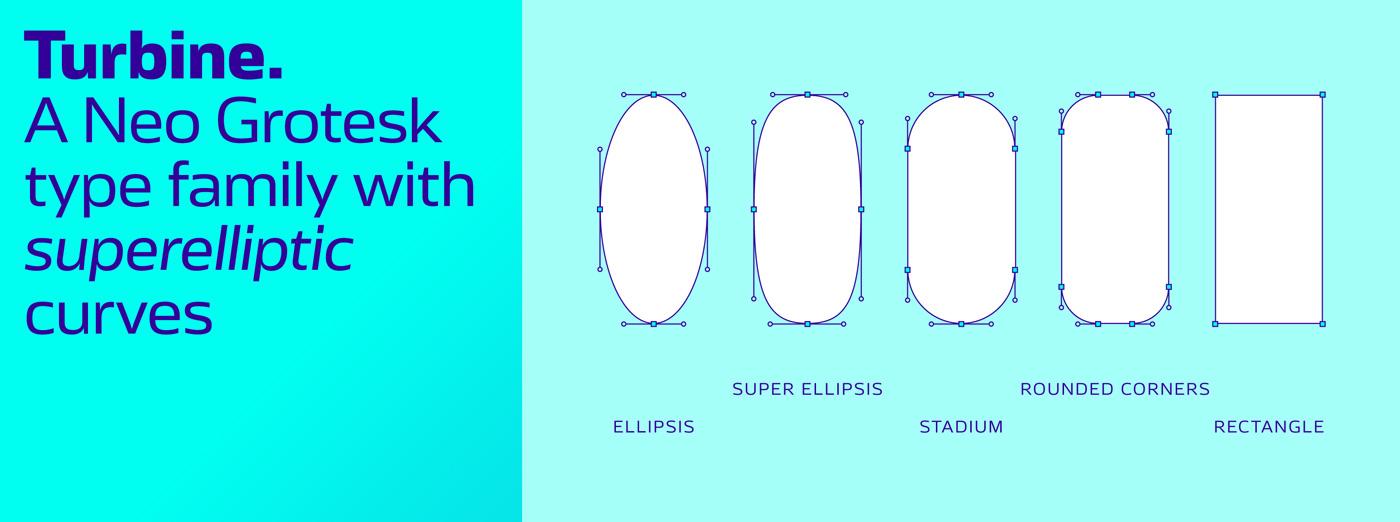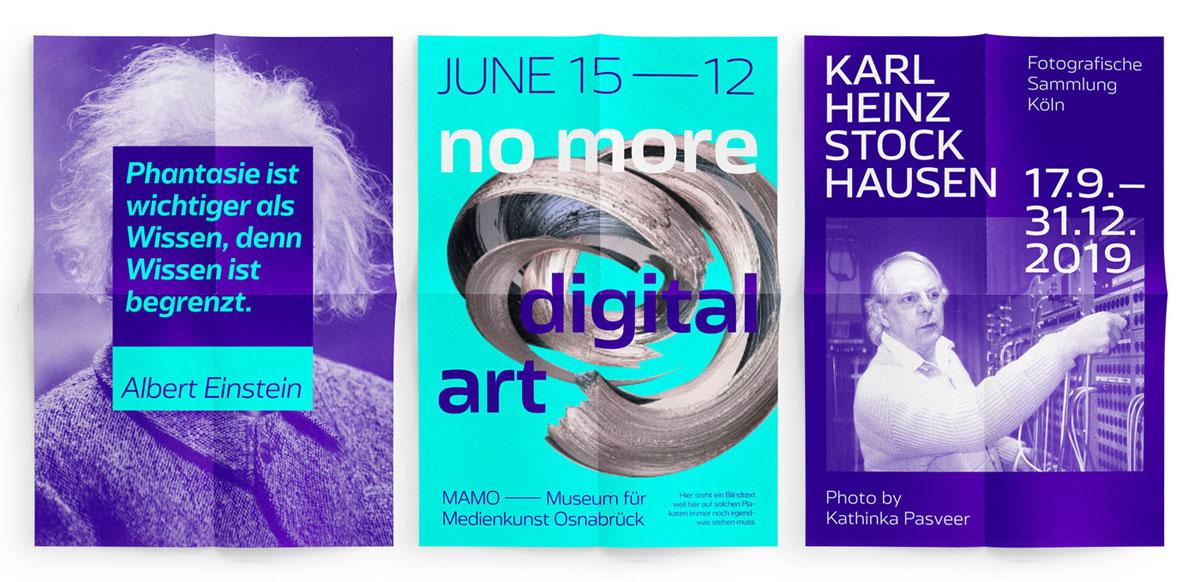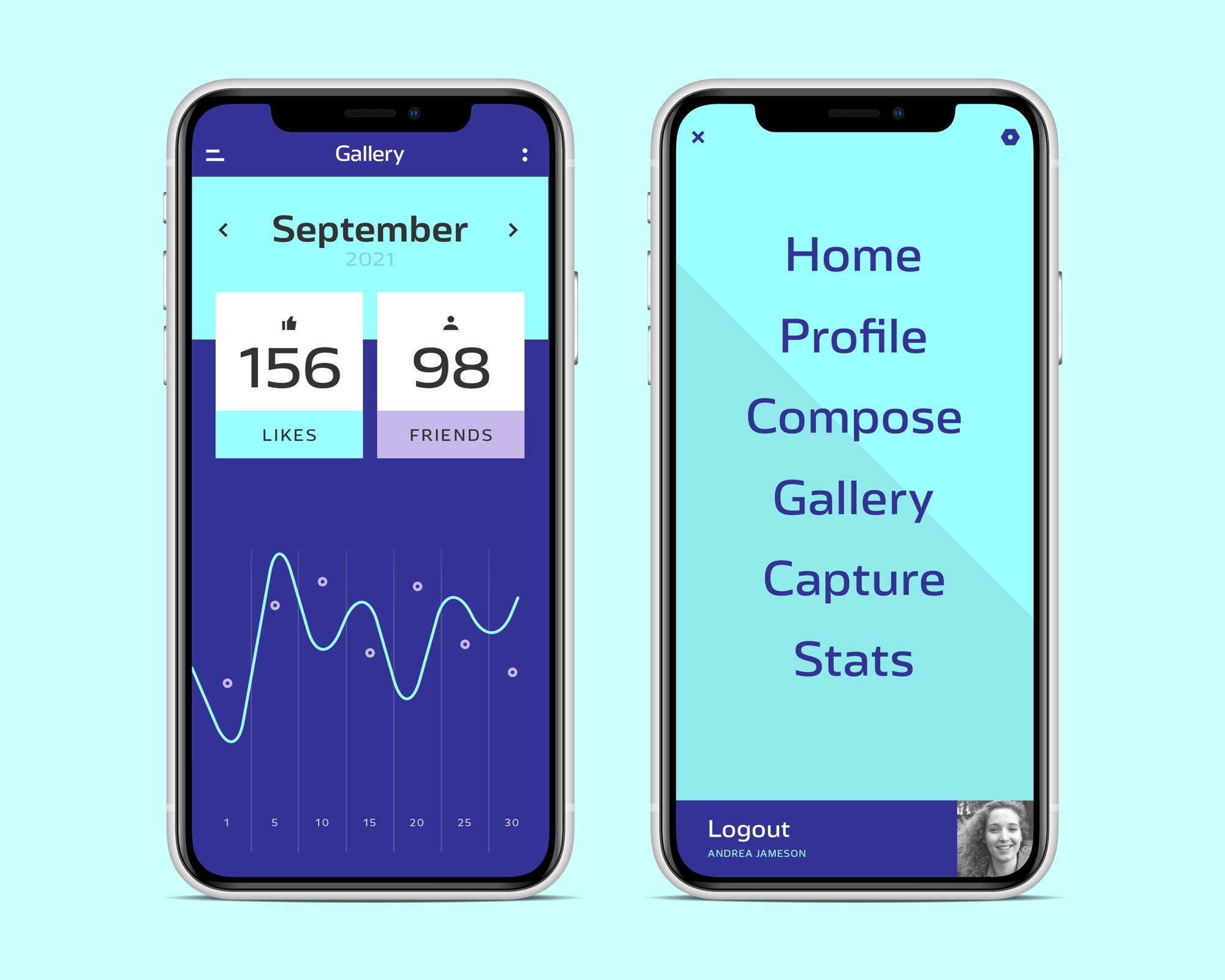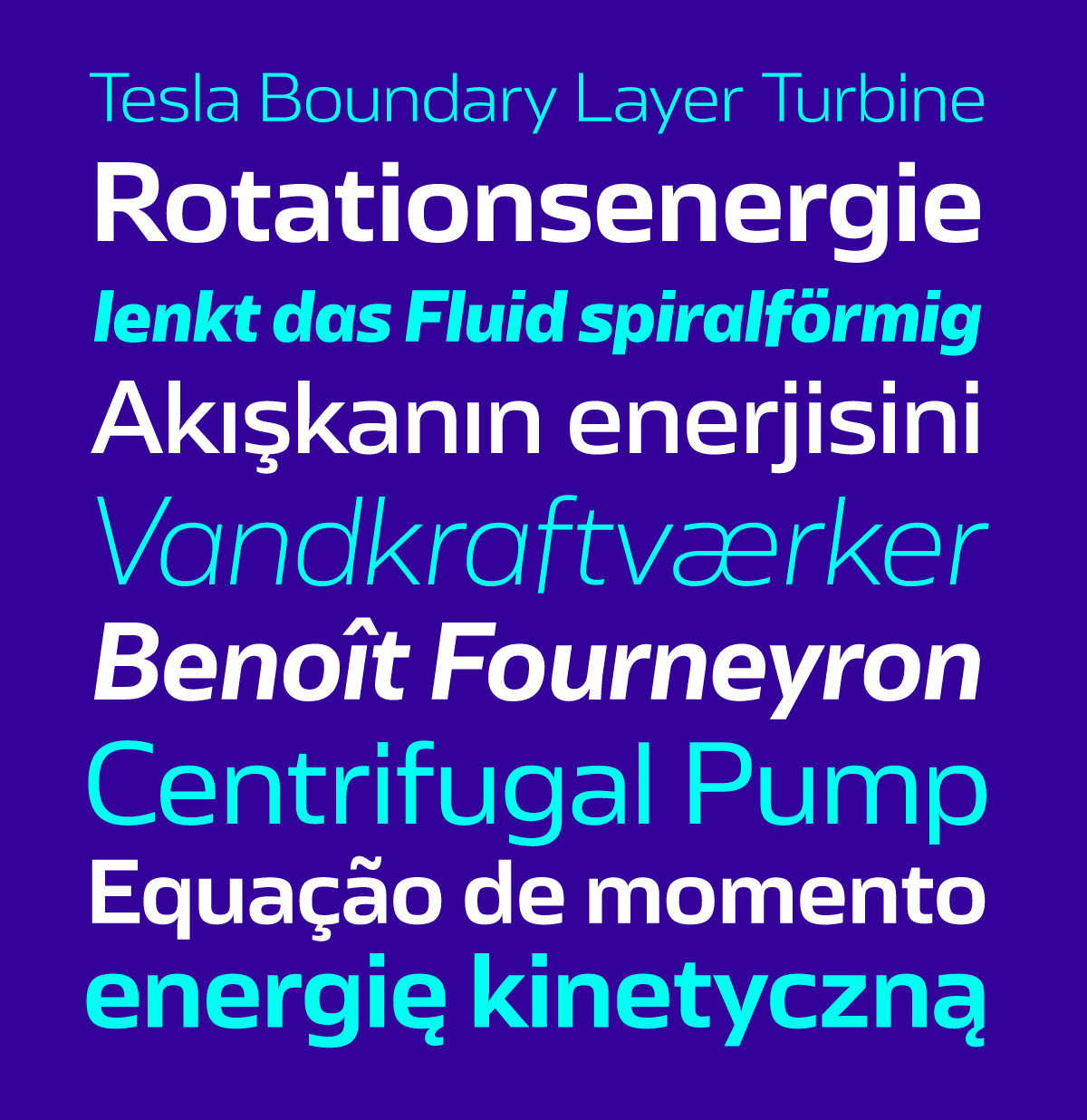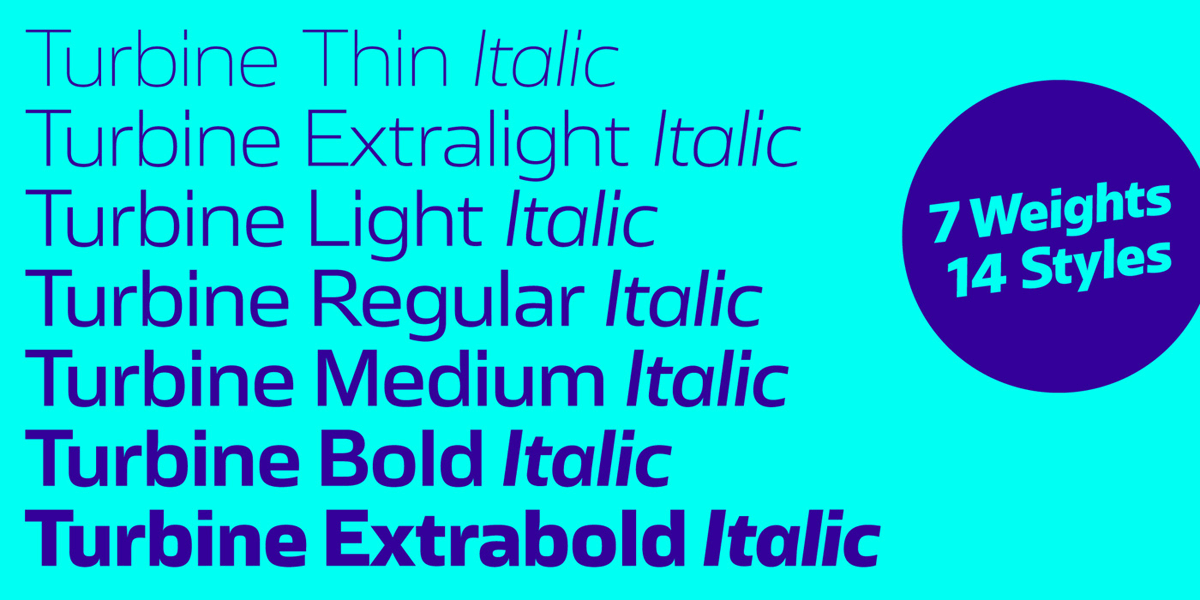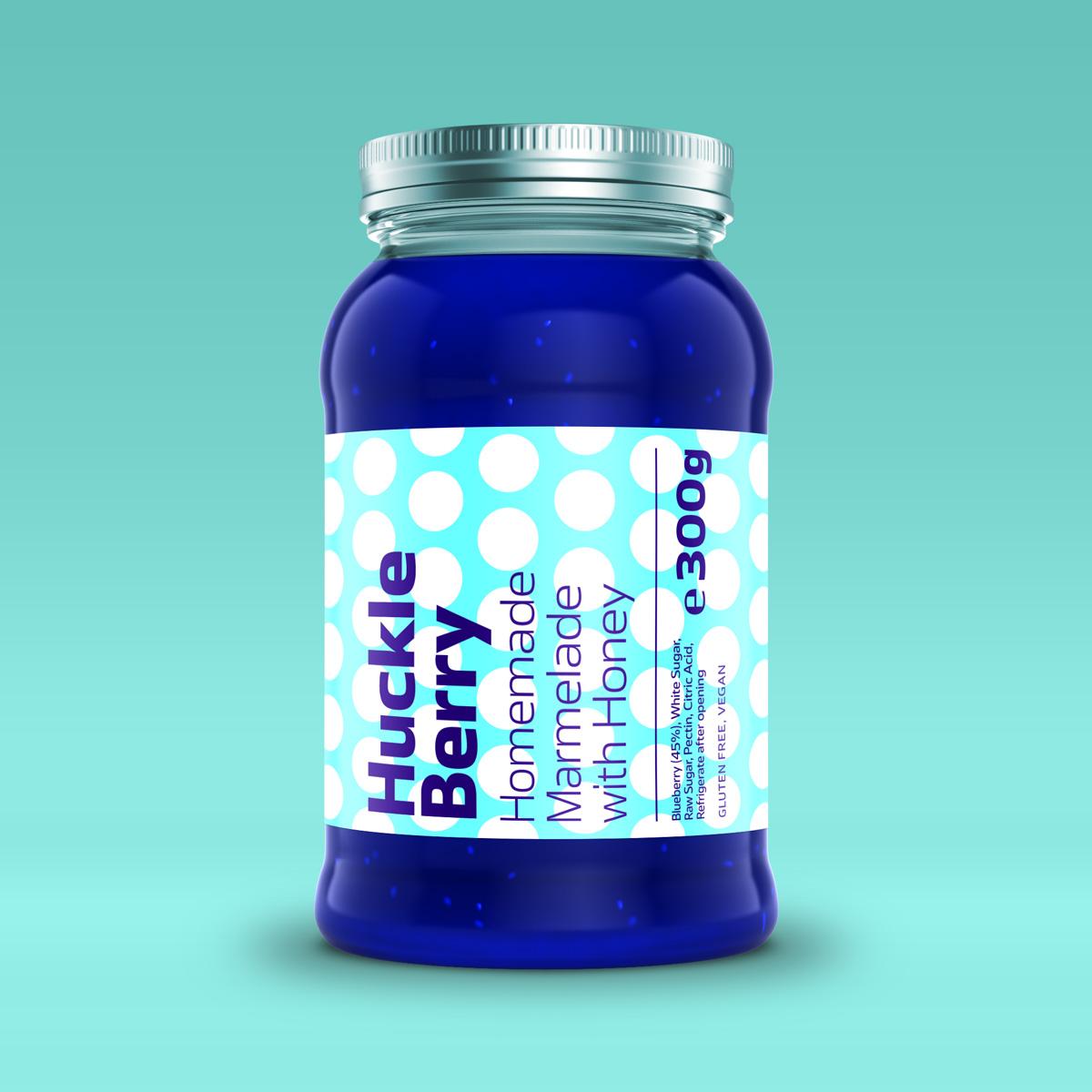
Turbine, die Schrift mit der speziellen Kurve
Alle Schriften von Felix Braden tragen einen Namen, der einen Bezug zu Wasser hat. Turbine folgt diesem Prinzip, und fokussiert die technischen Aspekte, die mit dem nassen Element assoziiert werden. Damit hebt der Kölner Designer diese Eigenschaft auch zugleich als wichtigstes Charakteristikum seiner Schrift hervor. Die markanten Kurven, die breiten Proportionen und der minimale Kontrast bewirken zudem ein rationales Auftreten mit hohem Wiedererkennungswert. Hervorragende Eigenschaften also für Corporate-Design-Projekte und Werbekampagnen, insbesondere von Auftraggebern aus Industrie, Maschinenbau, Technik und Pharmazie.
Turbine ist eine Neo-Grotesk mit superelliptischen Kurven. Die auch als Lamésche Kurve bekannte geometrische Besonderheit (eine Mischung aus Ellipse und Rechteck) steht in Architektur, Stadtplanung, Produkt- und Interior-Design für ein freundliches, sympathisches Erscheinungsbild. Da diese Art der Gestaltung in den 60ern und 70ern populär wurde, besitzt Turbine auch einen Retroaspekt. Allerdings weniger im nostalgischen, als vielmehr im futuristischen und Vertrauen erweckenden Sinne, denn ihre Gegenwartstauglichkeit steht außer Frage.
Die sehr offenen Formen der Neo-Grotesk erzielen verglichen mit älteren Schriften dieser Art eine deutlich höhere Leserlichkeit und Eleganz. Ein geringer Strichkontrast und an das Rechteck angenäherte Kurven funktionieren perfekt am Bildschirm und machen Turbine zu einem Allrounder auch für Webdesign und App-Design. Die Familie hat 7 Strichstärken, von Thin bis Extrabold plus entsprechender Kursiven.